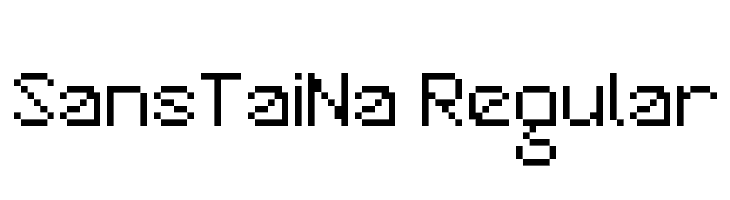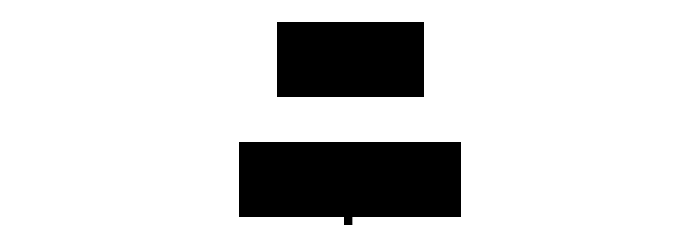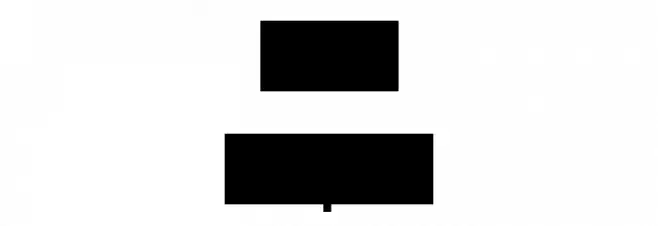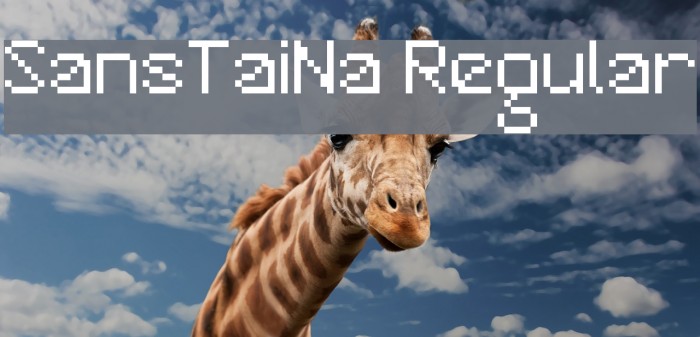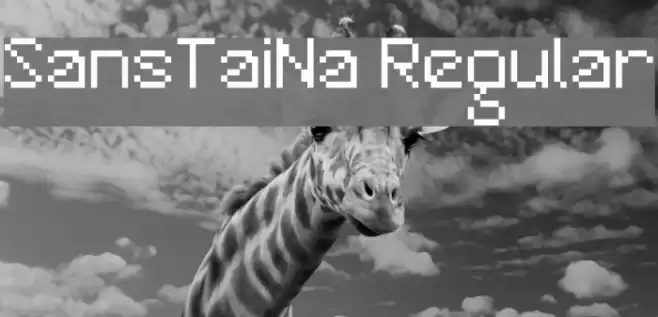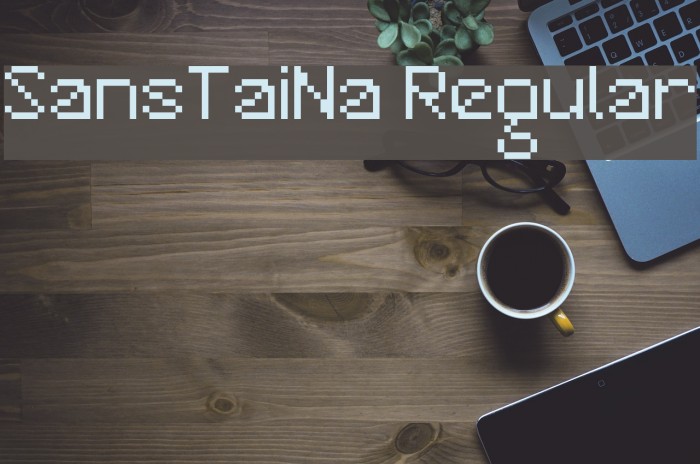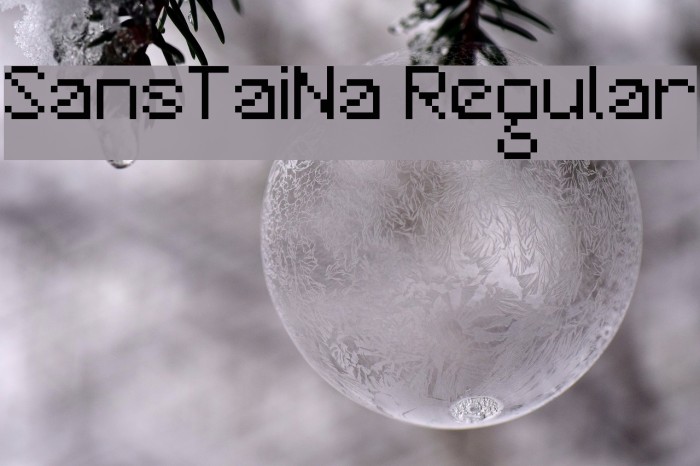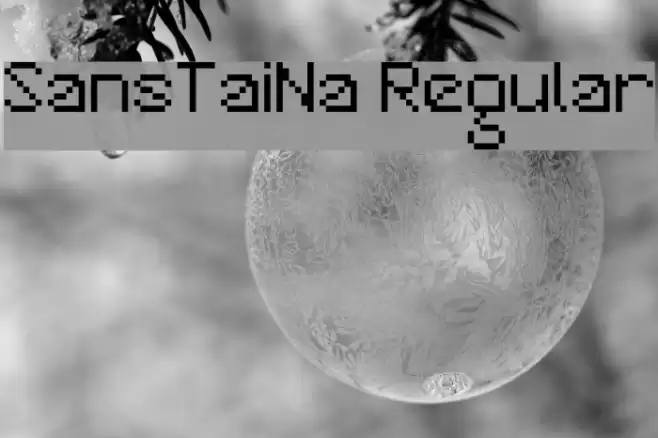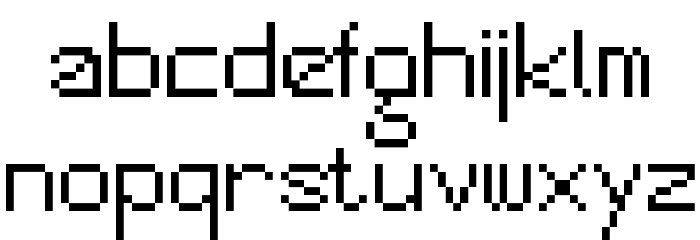
SansTaiNa Regular Font
✎ Pixel
| 名前 | SansTaiNa Regular |
| カテゴリ | Pixel |
| 全体的なスタイル | Retro, Digital |
| 用途 | Logos, Headlines, Digital Art |
| おすすめプロジェクト | Ideal for retro-themed designs, video game graphics, digital art projects, and any creative work that requires a nostalgic or tech-inspired look. |